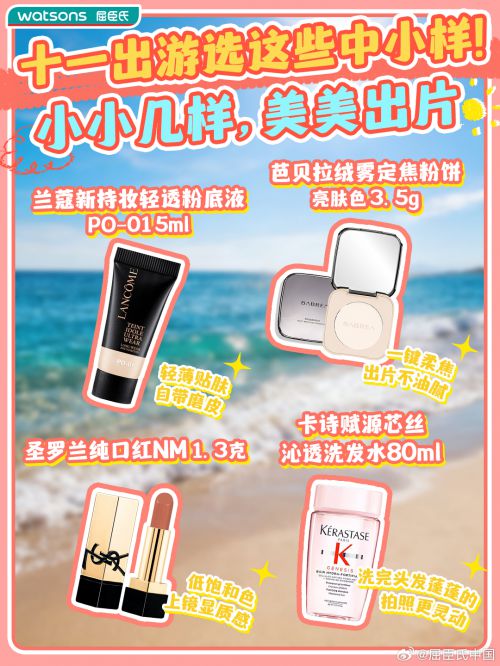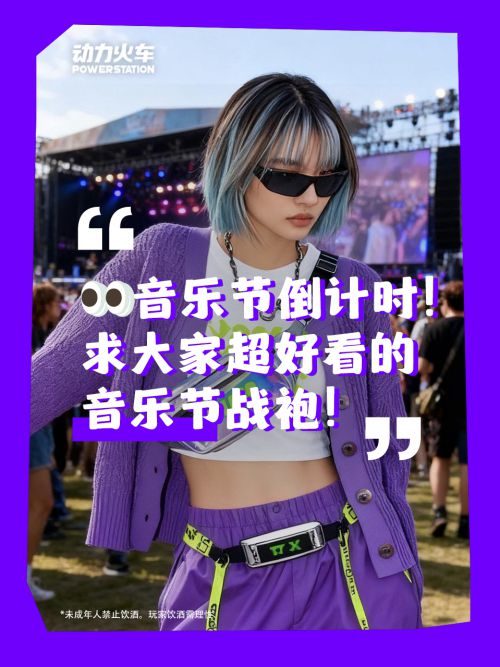
仓迹嘟嘟体
仓迹嘟嘟体是由仓迹字库推出的创意字体,以卡通有趣的风格在设计领域备受青睐。字体字形偏扁宽,重心居中且中宫宽博,整体结构稳重大方,又不失灵动巧思。笔画粗实均匀,笔型融入大量圆润设计,直线中巧妙点缀圆角,搭配气泡状装饰元素,既保留利落线条感,又传递出敦厚可亲的气质。圆头笔画与自然连笔过渡,让每个字都独具形态,而最具代表性的“勾”笔画,形似胖乎乎的小脚,小巧灵动,为字体注入俏皮活力。作为支持简体中文常规字符集的商用字体,仓迹嘟嘟体适用于儿童读物、文创产品、品牌宣传等场景,轻松传递趣味与温暖,是创意设计的理想之选。